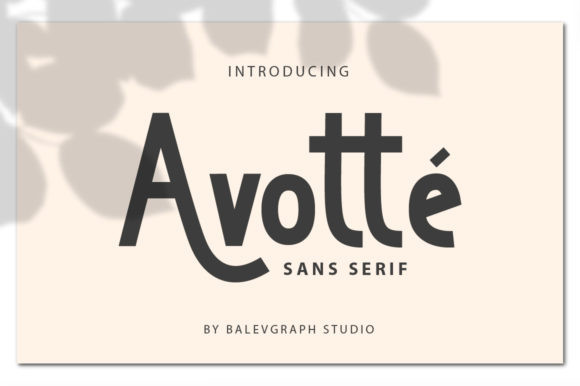
Creativefabrica Avotte Font
[Creativefabrica] Avotte Font
Avotte - это простой и современный шрифт без засечек.
Благодаря своей игривости он прекрасно подходит для творческих проектов, будь то вдохновляющие настенные плакаты или для распространения информации о вашем бренде.